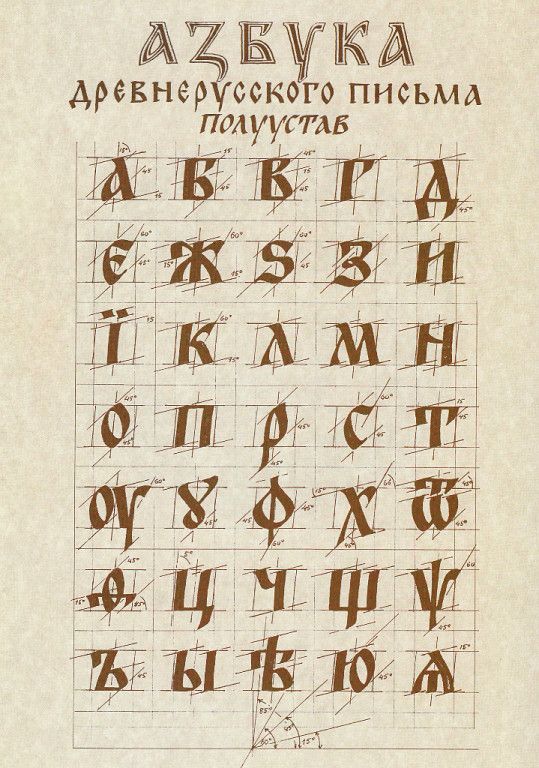
Шрифт русский древний: Старославянские шрифты — русские скачать бесплатно
Old Standard. Семейство Old Standard — многоязычный шрифт, который пригоден для исследовательских работ в области классической филологии. Old Standard воспроизводит специфическую разновидность классицистической антиквы (так называемый тип «Модерн»), которая весьма широко использовалась в различных изданиях конца XIX и начала XX в.
Monomakh Unicode — шрифт в стиле устава/полуустава.
Ponomar Unicode є҆́сть шрифтъ длѧ рабо́ты съ современными церковнославѧнскими текстами. Шрифтъ повторѧ́етъ гарнитꙋрꙋ и҆зꙿ изданїй Сѷнода́льной тѷпогра́фїи нача́ла XX вѣ́ка.
Хиландарски устав — шрифтъ сдѣланъ по просьбѣ бра́тства монастырѧ̀ Хиландара на ѻсновѣ бо́лѣе ѿ҃ рꙋкописей перїода в҃і-є҃і вв. и҆зъ монастырской ризницы. соде́ржитъ ѻколо 4500 глифовъ.